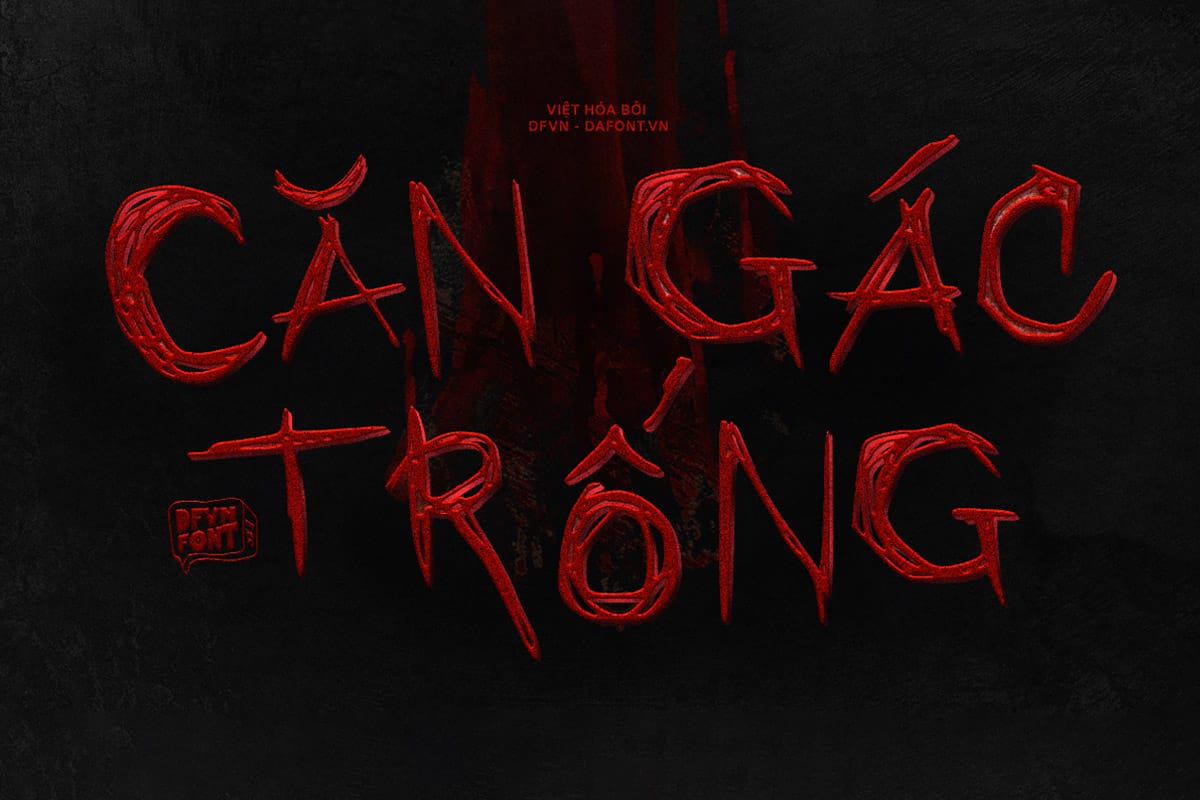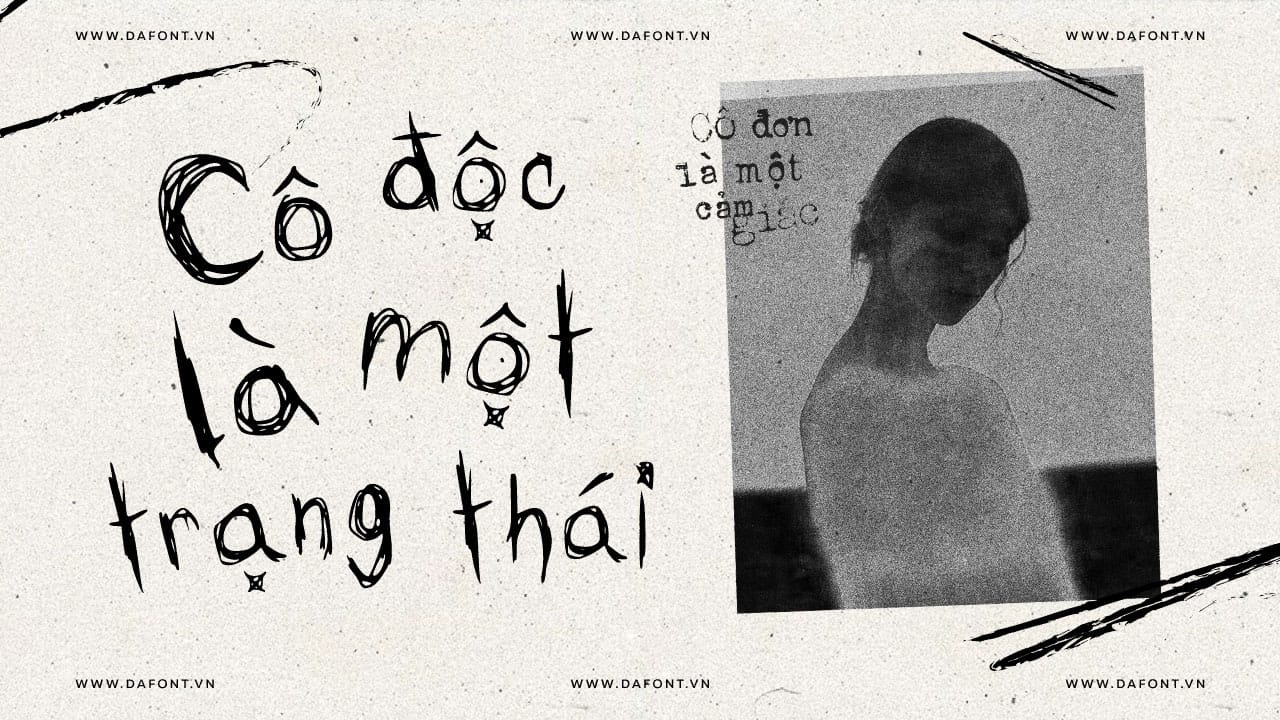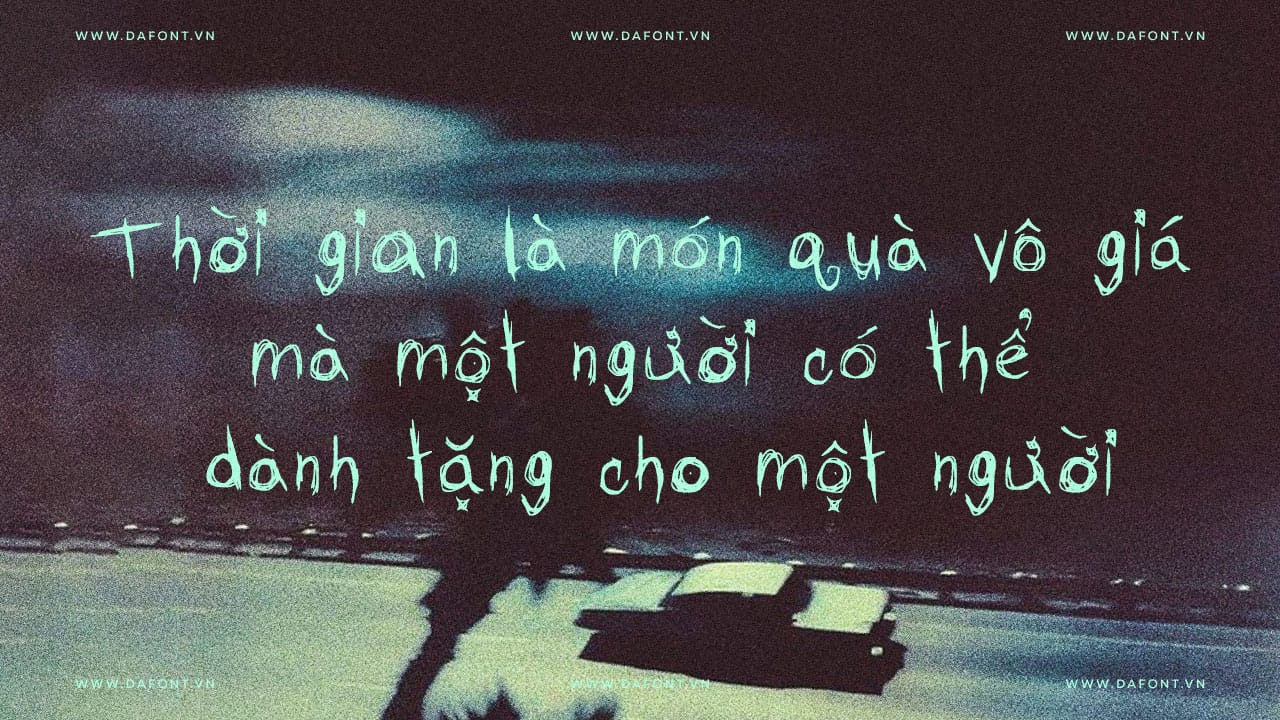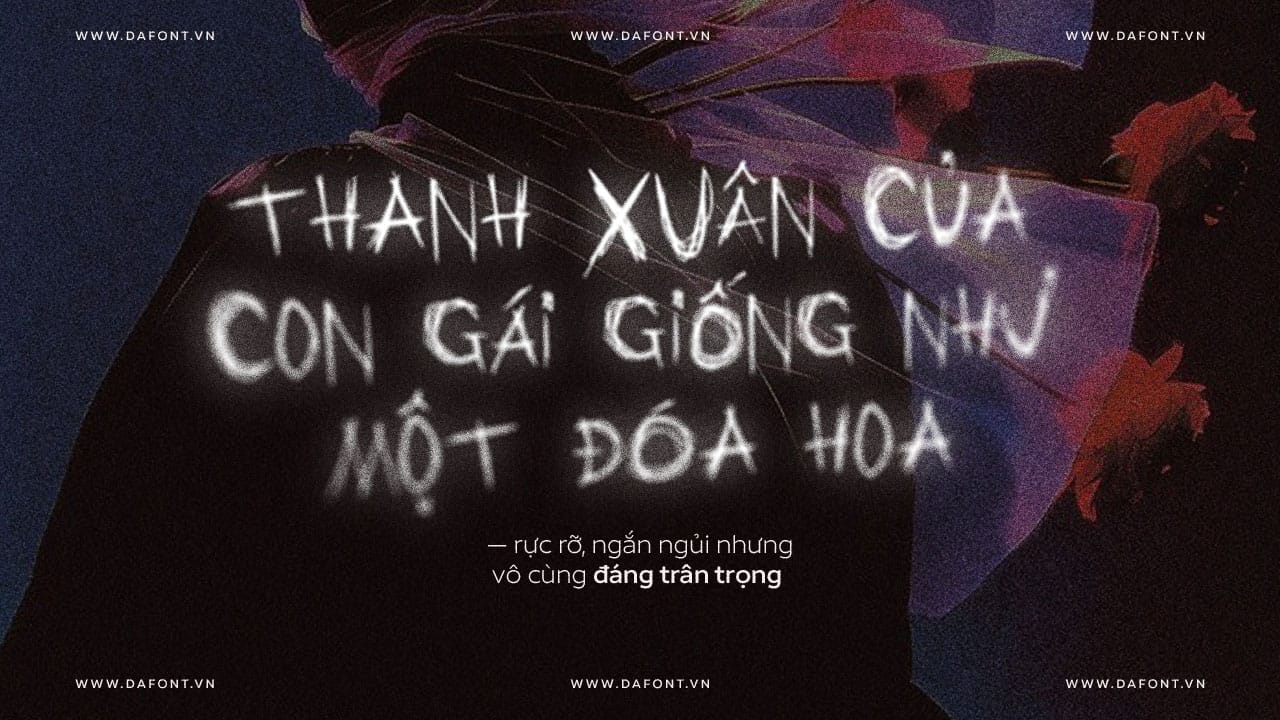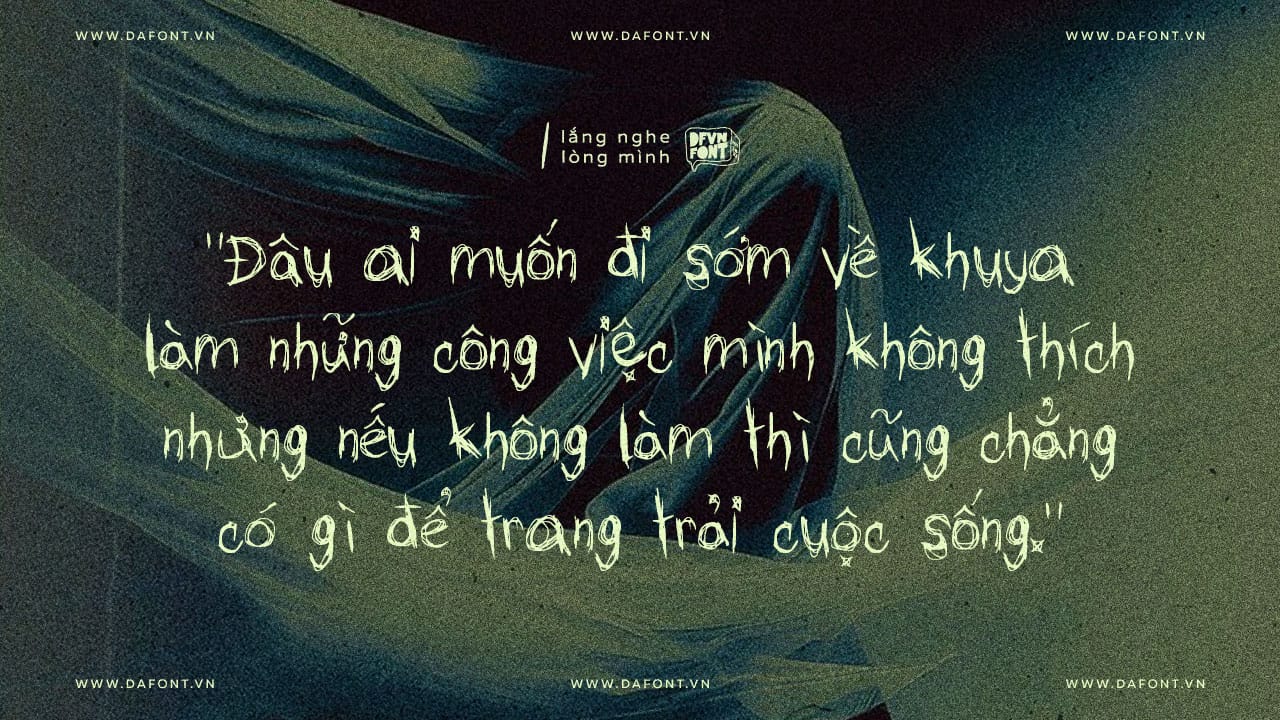
DFVN The Typing of a Madman Việt hóa
DFVN The Typing of a Madman là một display/script font phong cách “trash” giả lập chữ đánh máy nguệch ngoạc, phù hợp cho thiết kế kinh dị, poster phim, bìa album và đồ họa cần cảm giác hỗn loạn, gai góc, DIY, underground hoặc nghệ thuật đường phố.
Font này ban đầu được tạo ra như một bài kiểm tra thử nghiệm, nhưng vì kết quả khá tốt nên nhà thiết kế quyết định chia sẻ công khai. Nó mang phong cách “điên loạn” với các nét chữ không đều, giống như được gõ trên máy đánh chữ cũ kỹ, tạo cảm giác hỗn loạn và nghệ thuật.
Đặc điểm nổi bật của DFVN The Typing of a Madman
DFVN The Typing of a Madman là một kiểu chữ mang phong cách grunge / trash đặc trưng, lấy cảm hứng từ máy đánh chữ cũ kỹ kết hợp với nghệ thuật scribble thô mộc. Font mang đến cảm giác hỗn loạn nhưng đầy chủ ý – giống như được gõ ra trong khoảnh khắc điên loạn giữa cảm xúc và lý trí.
Dưới đây là những điểm khiến font này trở nên khác biệt:
• Phong cách grunge độc đáo: Font mang hơi hướng “trash / scribble”, mô phỏng nét chữ nguệch ngoạc của máy đánh chữ cũ, tạo cảm giác cũ kỹ, bụi bặm và điên loạn.
• Nét chữ bất quy tắc, giàu biểu cảm: Mỗi ký tự được thiết kế với độ nghiêng, độ dày mỏng và khoảng cách ngẫu hứng – thể hiện tinh thần tự do, không rập khuôn, phù hợp cho các chủ đề kinh dị, tâm lý, nghệ thuật đường phố, hay dự án mang hơi hướng nổi loạn.
• Cảm hứng từ máy đánh chữ cổ: Font được lấy cảm hứng từ những cú gõ máy đánh chữ cũ kỹ, tạo nên nét rung, lệch nhẹ và “vết mực” ảo trên từng ký tự – khiến văn bản trông như được gõ thật trên giấy.
• Phù hợp cho tiêu đề và thiết kế sáng tạo: Do phong cách mạnh và chi tiết phức tạp, font lý tưởng cho poster, tiêu đề, bìa album, tạp chí nghệ thuật hoặc các dự án mang tính cá nhân.
• Việt hóa tinh chỉnh bởi DFVN: Font được bổ sung đầy đủ dấu tiếng Việt cùng kerning cân đối, đảm bảo khả năng hiển thị ổn định mà không làm mất đi chất “scribble nguyên bản”.
The Typing of a Madman là kiểu chữ grunge / typewriter scribble độc đáo – kết hợp giữa sự hỗn loạn và tính nghệ thuật, lý tưởng cho những ai muốn phá vỡ khuôn mẫu và tạo ấn tượng mạnh trong thiết kế.